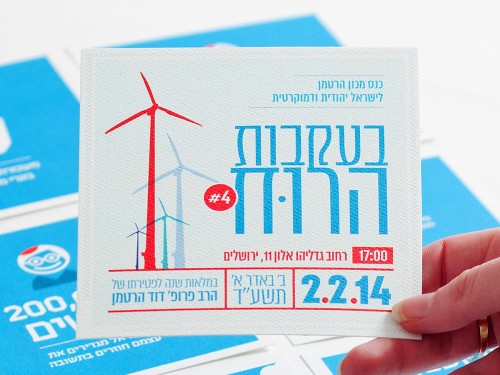
אחיו הצר של פונט אמביוולנטי הוא פונט הרפתקן ושאפתן בעל צורניות נעימה ומפתיעה
אמביוולנטי צר חולש על שני קוטבי הספקטרום. מצד אחד הוא נועז, אנרגטי ומפתיע, ומצד אחר אופיו יציב, בטוח ומוקפד
הפונט שואב את השראתו הסגנונית מגופנים לטיניים מקטגוריית הסלאב־סריף. תהליך העבודה על הגופן ארך יותר משלוש שנים, שבמהלכן הוא התפתח ועבר שינויים ושיפורים רבים.